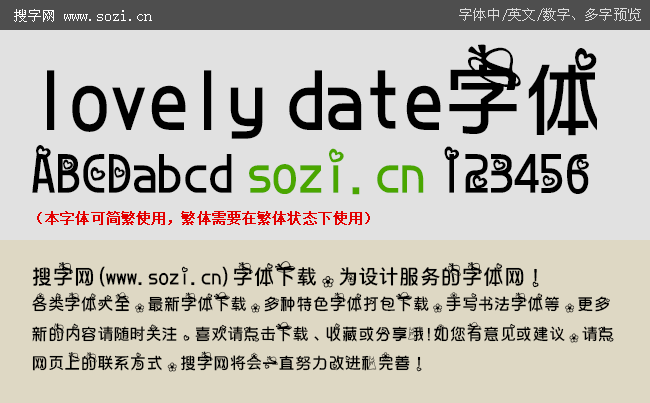
lovely date字體
搜字網(wǎng)給大家提供一款很卡通的手機(jī)中文字體下載。修改者給這款字體叫l(wèi)ovely date字體,這款手機(jī)中文字體以POP字體為原形,在筆畫間嵌入了可愛的卡通圖形,該中文字體趣味性強(qiáng),又保持了文字的識(shí)別度,非常適合喜歡卡通的朋友在手機(jī)上安裝使用。